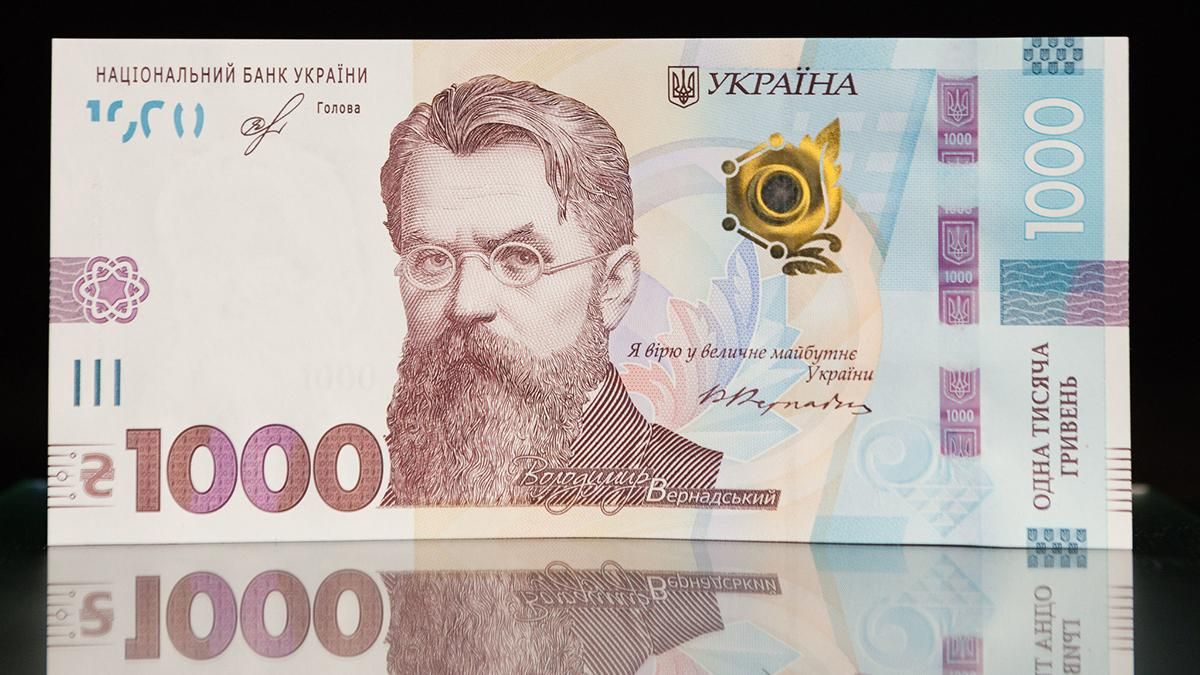
Дизайнер Богдан Гдаль зазначив, що мова йде про кириличну версію шрифту Bickham Script Pro 3, який розробили дизайнери Adobe. Версію цього шрифту випустили лише у 2016 році.
До цього часу в інтернеті поширювались "піратські", тобто, неофіційні версії цього шрифту. Одну з них і використали у Національному банку. Цим шрифтом написані слова "Одна тисяча гривень" на звороті банкноти.
Чим відрізняється оригінальний шрифт від фейкового? Відрізняються вони розміром букви "в" у слові "гривень". В оригінальному шрифті "хвостик" цієї букви є дещо меншим та не таким широким, а "в" у "піратській" версії шрифту така ж, яка зображена на українській банкноті.
Різниця між оригінальним та фейковим шрифтом на банкноті 1000 гривень
Український дизайнер Богдан Гдаль уже зв'язався з автором шрифту Річардом Ліптоном, який перенаправив його на дизайнера компанії Adobe. Останній підтвердив, що на банкноті 1000 гривень і справді розміщено напис неоригінальним шрифтом.
Шкода, що Національний банк України не помітив недоліків шрифту, про який йде мова. І це, безумовно, не Bickham Script Pro 3. В будь-якому разі, наша ліцензія не дозволяє вносити зміни у шрифт,
– повідомили у компанії Adobe.
Наразі у компанії не коментують, чи будуть позиватися до НБУ через порушення авторського права.